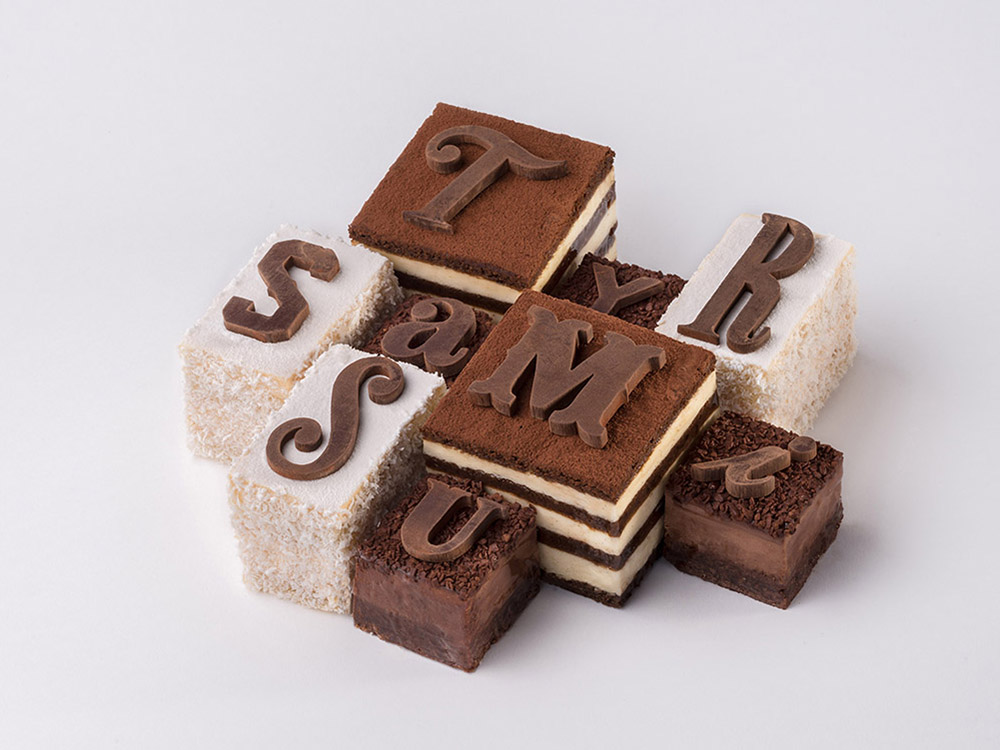
Los tipos comestibles de Castel
Tyramisu es fruto de la unión de dos disciplinas creativas aparentemente tan distantes como pueden ser la pastelería y la tipografía. Se trata de una reinterpretación insólita del tradicional postre italiano que han creado conjuntamente el chef Benoit Castel y el reconocido diseñador parisino Tyrsa. La experimentación culinaria del chef, que combina tres recetas diferentes de tiramisú (clásica, con chocolate y con fruta de la pasión), se comunica también a nivel visual, pues la atípica presentación del dulce permite distinguir entre los tres tipos de tiramisú. Además, cada uno de los carácteres de chocolate creados por Tyrsa contribuyen a delimitar los sabores de las porciones.